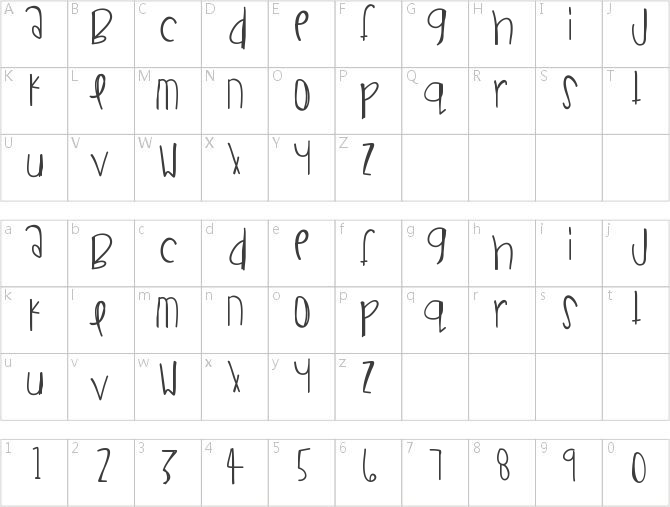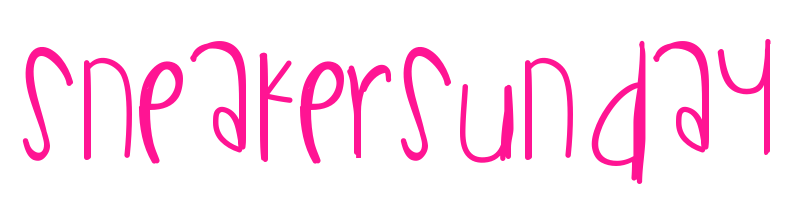
字體名稱: Sneaker
SneakerSunday
SneakerSunday字體字庫(kù)是一款讓人賞心悅目、百看不厭的英文字體,適合各類廣告和產(chǎn)品包裝設(shè)計(jì)應(yīng)用,字體大小0.03MB,格式為ttf字體,上傳用戶是Who am I?,作者/版權(quán)方為未知